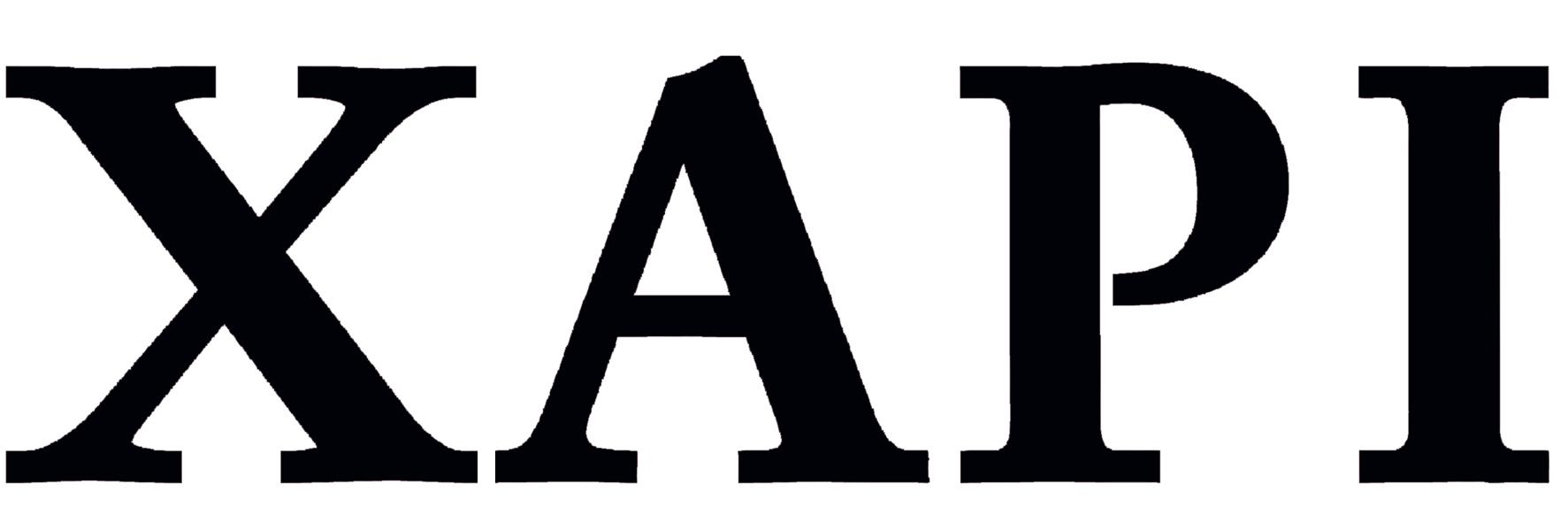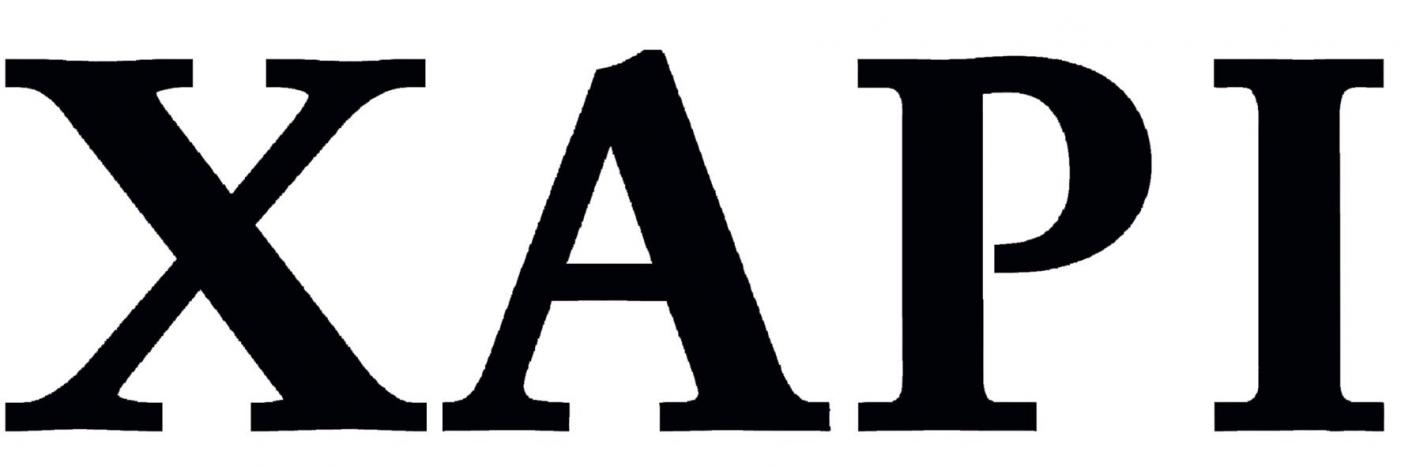
Suche Schrift ähnlich der Garamond
ich suche Die Schrift auf folgendem Bild:
Das A sieht aus wie von einer Garamond aber die Serifen sind nicht so eckig.